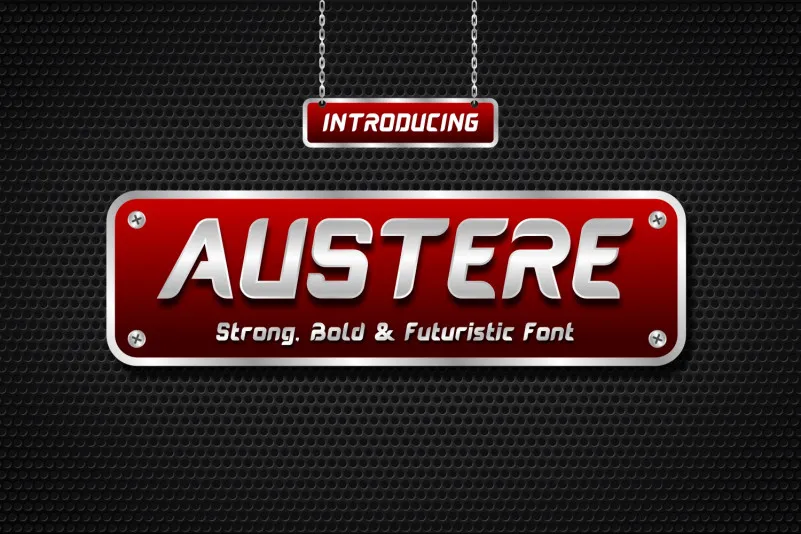
Austere Display Font – Download Grátis
Austere Display Font é uma tipografia display que transmite modernidade futurista e atitude esportiva. Seja ele quem você for, ou seja qual for o projeto, este tipo traz um estilo único, perfeito para destacar sua marca ou mensagem de forma impactante no design gráfico. Em uma era digital sempre rápida e em constante evolução, Austere Display Font está preparado para levar seu trabalho ao nível seguinte. Com uma paleta de linhas aguçadas e linhas finas que se encaixam perfeitamente com qualquer ambiente visual, esta fonte é ideal para criar mensagens assertivas e impactantes. Seja ela a sua escolha para headlines, textos de destaque ou pequenas detalhes em seu design, Austere Display Font garante um estilo único e inovador, adequado tanto para projetos profissionais quanto pessoais.